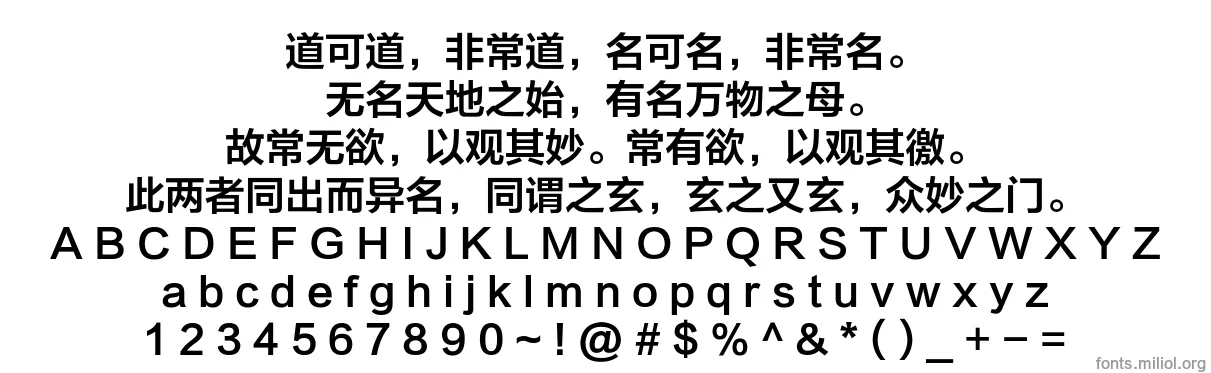
《方正兰亭中粗黑_GBK:经典字体的设计与应用》
方正兰亭中粗黑_GBK(FZLanTingHeiS-DB1-GBK)是一款兼具现代感与实用性的中文字体,隶属于方正兰亭黑系列。其笔画粗壮有力,结构严谨,在标题、广告、品牌标识等场景中表现尤为突出。GBK编码支持广泛的汉字字符集,确保简繁体混排时的兼容性,适合印刷、数字媒体等多平台使用。
字体设计上,兰亭中粗黑延续了兰亭黑家族简洁大方的风格,横竖笔画对比鲜明,转折处略带弧度,既保留了黑体的稳重,又增添了一丝灵动。无论是大幅海报还是UI界面,都能清晰传递信息,提升视觉层次感。作为一款商业授权字体,用户需通过正规渠道获取授权,以确保合法使用。
方正兰亭中粗黑_GBK 字体映射图